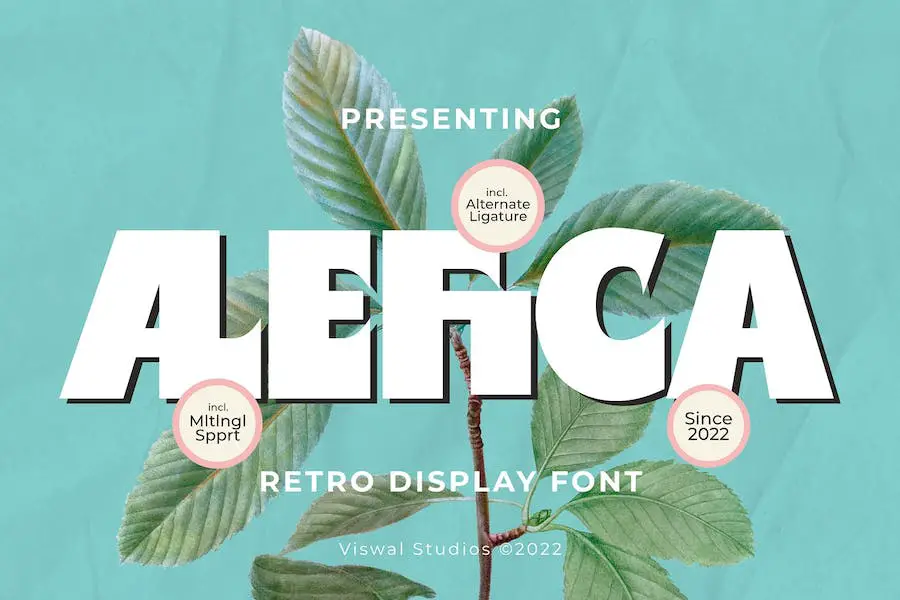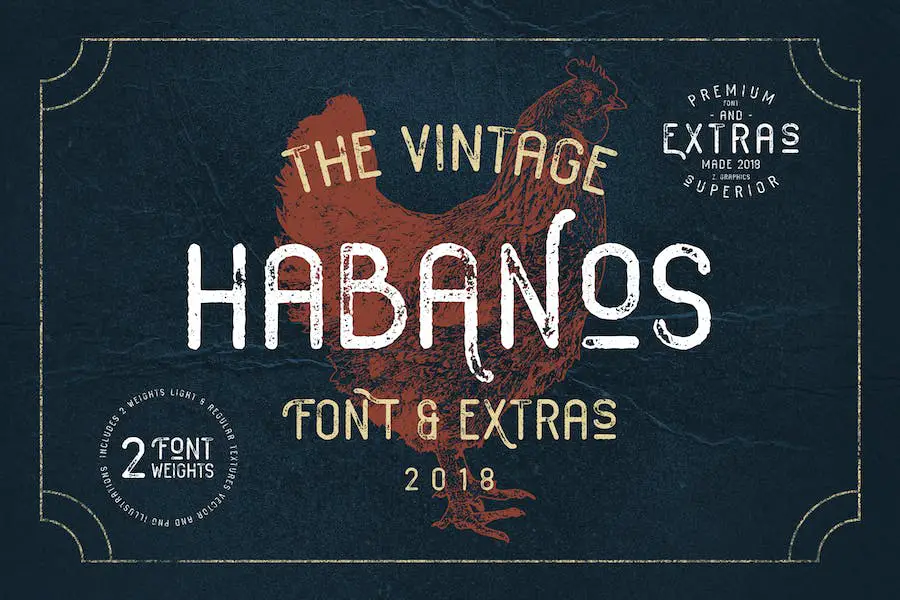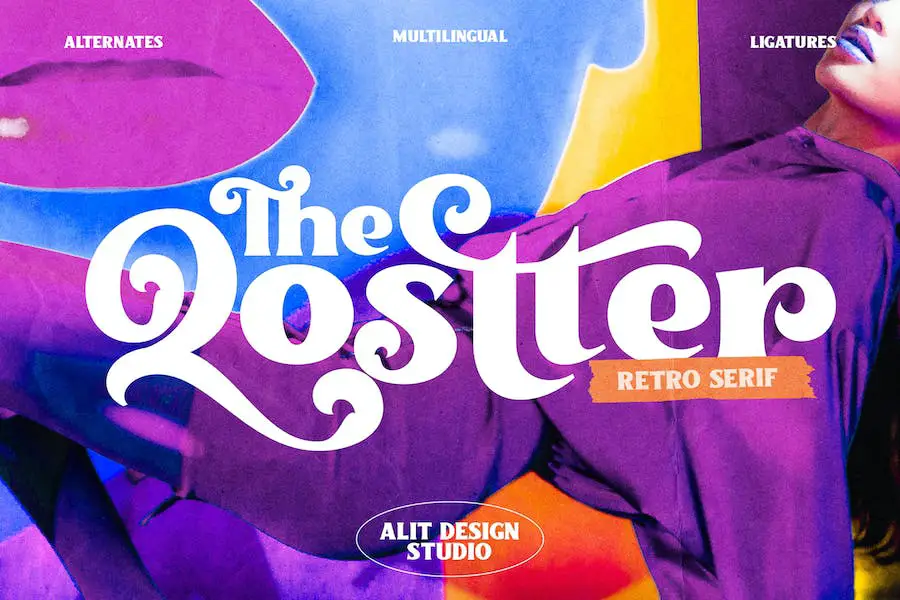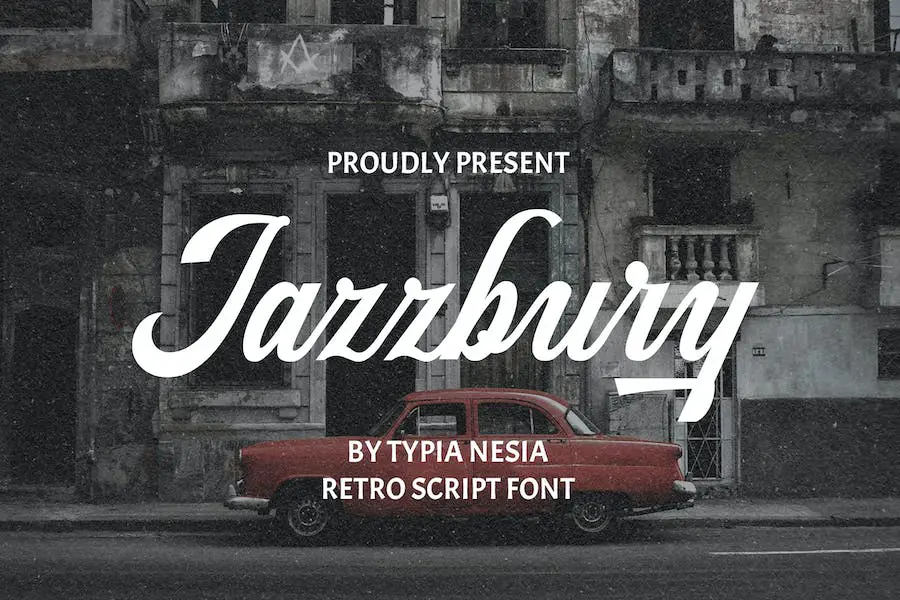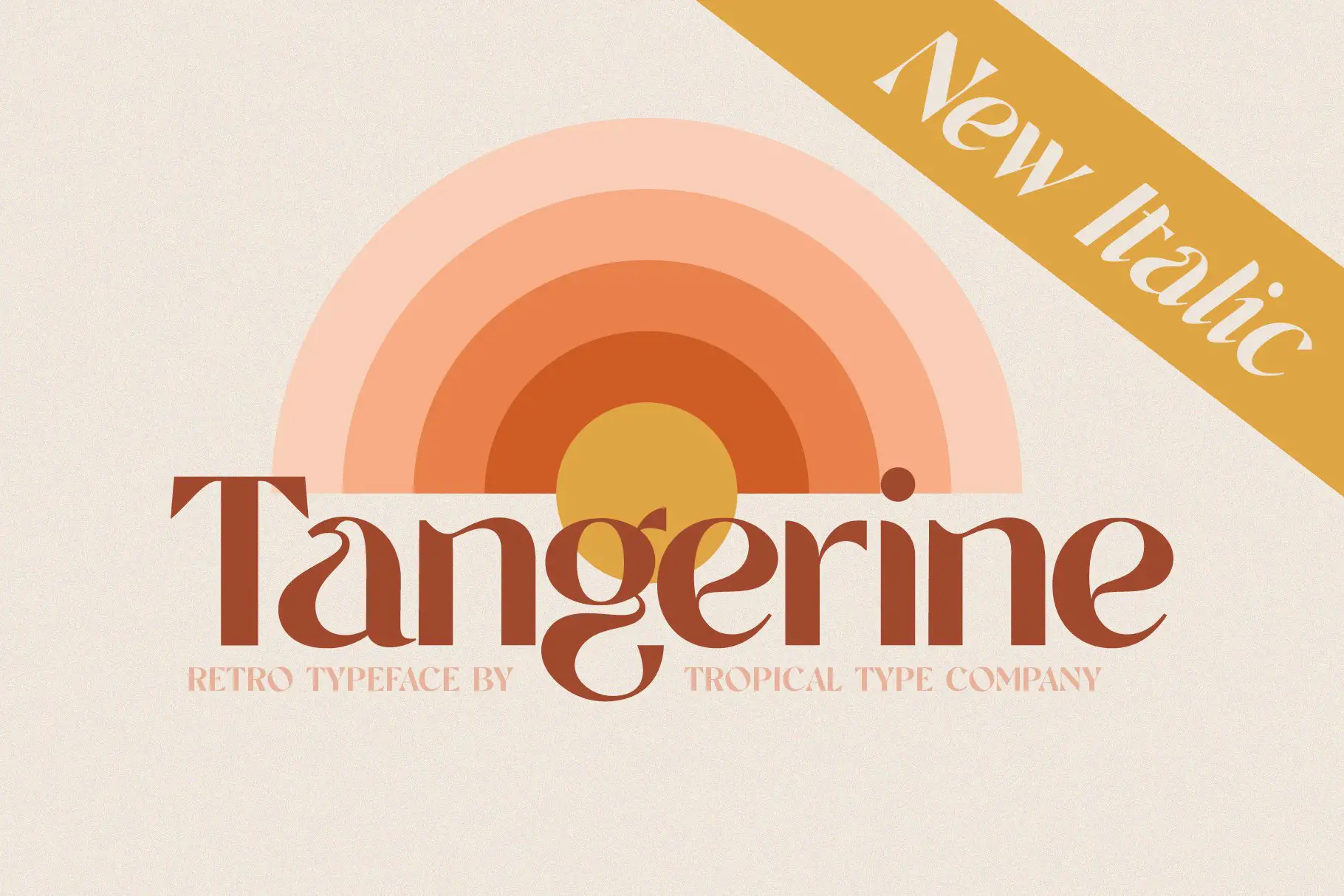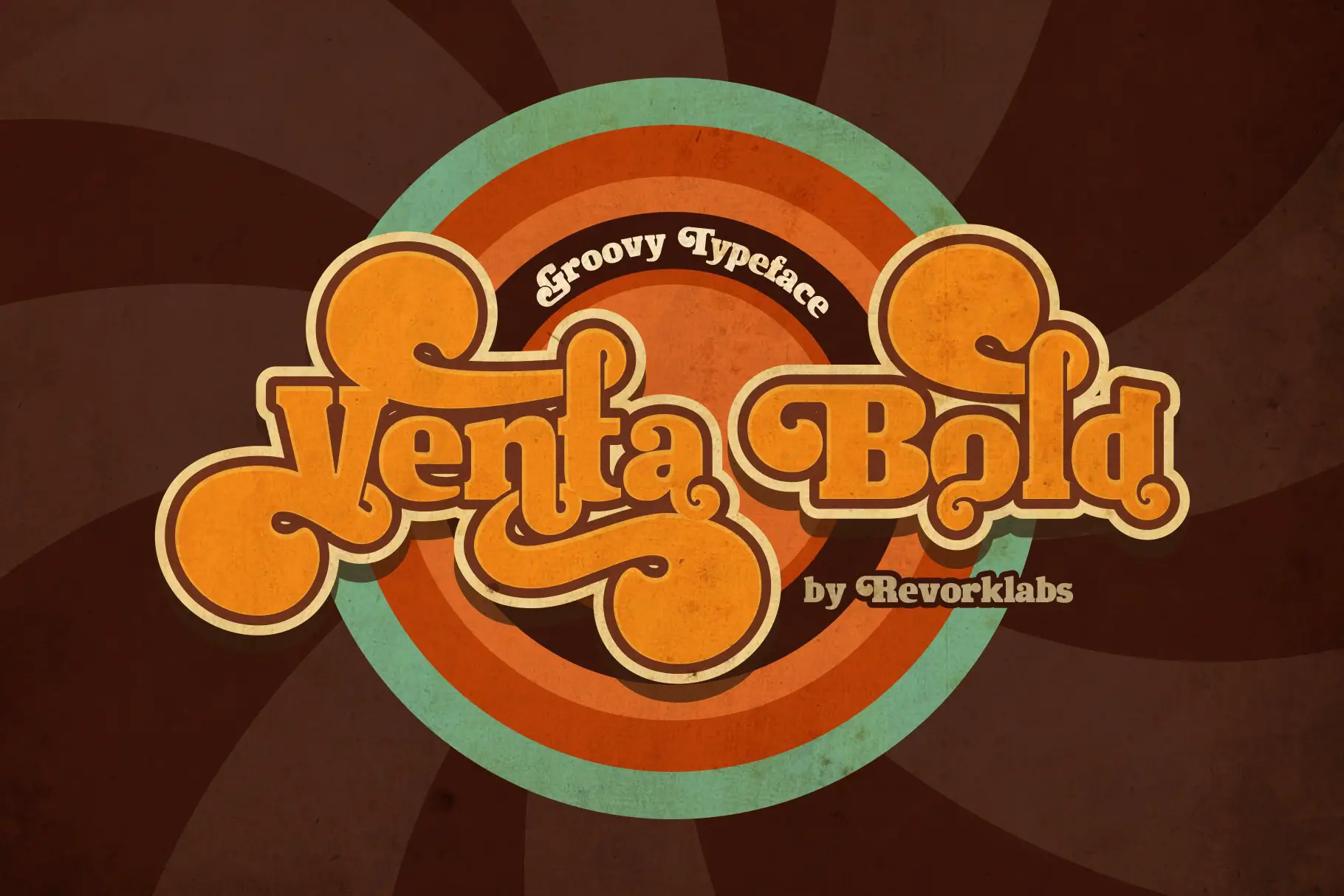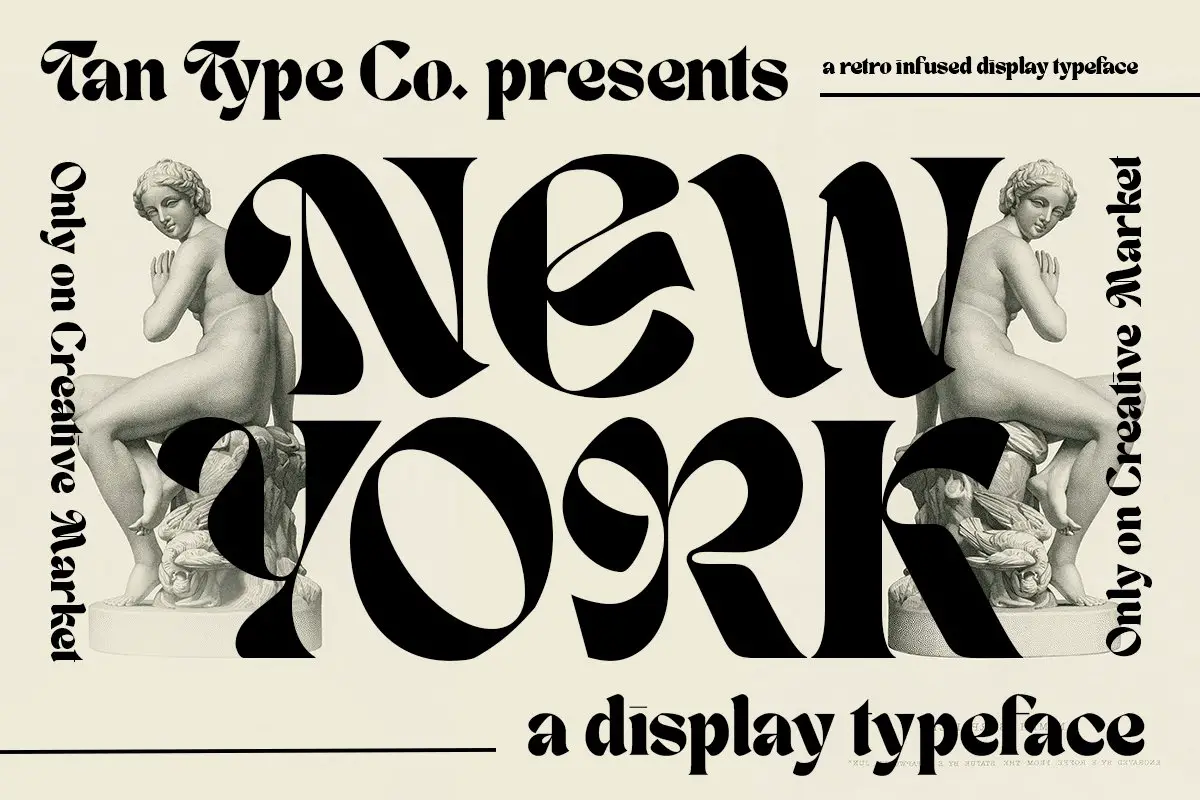
Die 36 besten Retro-Schriftarten 2023 (kostenlos und Premium)
Veröffentlicht: 2023-05-21Möchten Sie Ihren Designs etwas Retro-Flair verleihen und sie von der Masse abheben? Suchen Sie nicht weiter, denn wir haben für Sie eine Liste der 36 besten Retro-Schriftarten zusammengestellt!
In diesem Artikel stellen wir eine handverlesene Auswahl der besten Retro-Schriftarten vor, die derzeit auf dem Markt erhältlich sind.
Diese Schriftarten wurden sorgfältig aufgrund ihrer Beliebtheit, Vielseitigkeit und Ästhetik ausgewählt. Egal, ob Sie an einem Branding-Projekt, einem Posterdesign oder einem Website-Layout arbeiten, diese Schriftarten verleihen Ihrer Arbeit mit Sicherheit das gewisse Etwas.
Was genau ist also eine Retro-Schriftart? Eine Retro-Schriftart ist eine Schriftart, die von einer bestimmten Epoche oder einem bestimmten Stil aus der Vergangenheit inspiriert wurde.
Diese Schriftarten werden oft in Vintage- oder Retro-Designs verwendet, können aber auch in moderneren Designs verwendet werden, um ihnen ein einzigartiges und nostalgisches Gefühl zu verleihen. In diesem Artikel erkunden wir eine große Auswahl an Retro-Schriftarten, darunter Art Deco, Mid-Century Modern und von den 1970er Jahren inspirierte Designs.
Also lasst uns anfangen!
Beste Premium-Retro-Schriftarten
In diesem Artikel stellen wir eine handverlesene Auswahl der besten Retro-Schriftarten vor, die heute auf dem Markt erhältlich sind. Diese Schriftarten wurden sorgfältig aufgrund ihrer Beliebtheit, Vielseitigkeit und Ästhetik ausgewählt.
Egal, ob Sie an einem Branding-Projekt, einem Posterdesign oder einem Website-Layout arbeiten, diese Schriftarten verleihen Ihrer Arbeit mit Sicherheit das gewisse Etwas.
In diesem Artikel erkunden wir eine große Auswahl an Retro-Schriftarten, darunter Art Deco, Mid-Century Modern und von den 1970er Jahren inspirierte Designs. Also lasst uns anfangen!
Rambors
Rambors ist eine mehrzeilige Displayschrift, die das flippige und futuristische Design der 70er-Jahre verkörpert. Diese Schriftart wirkt nostalgisch und zugleich zeitgenössisch und eignet sich daher perfekt für modern-futuristische Designs.
Eines der besten Features von Rambors sind die wechselnden Charaktere, die den Benutzern mehr Möglichkeiten zur individuellen Gestaltung ihrer Designs bieten. Diese Schriftart ist ideal für diejenigen, die nach Vintage-Schriftarten suchen, um ihren Projekten einen Hauch von Nostalgie zu verleihen und gleichzeitig eine moderne Atmosphäre zu bewahren.
Derphace
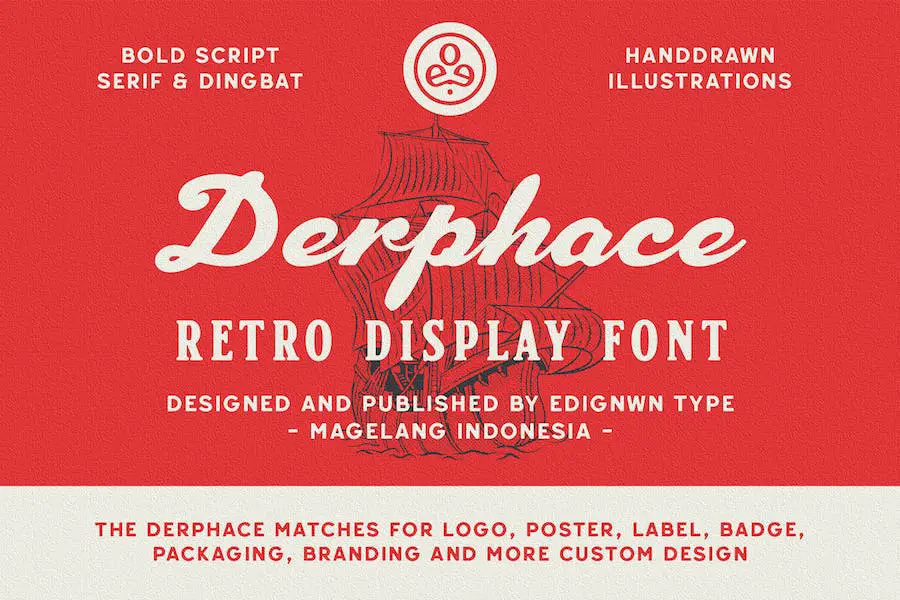
Derphace Font ist die perfekte Wahl für alle, die eine Schriftartensammlung im Retro-Stil suchen, um ihre individuellen Designprojekte aufzuwerten. Diese Schriftart ist von den alten Etiketten inspiriert und verfügt über Skript- und Serifenschriftstile.
Derphace Font umfasst vier einzigartige Schriftarten: Regular, Rounded, Rough und Stamp. Darüber hinaus bietet diese Schriftartensammlung zusätzliche Illustrationen zu nautischen und Piratenthemen in einem Paket.
Die Schreibschrift von Derphace bietet auch einige Alternativen, die für die Erstellung auffälliger Logos, Poster, Etiketten, Abzeichen, Verpackungen, Brandings, Zitate und mehr nützlich sein können. Seine Vielseitigkeit und vielfältigen Stiloptionen machen es zu einem Muss für jeden Designer, der nach Adobe Retro-Schriftarten sucht.
KABOORE
Kaboore ist eine neue Retro-Schriftart, die sich perfekt für Grafikdesigner eignet, die ihre Projekte aufwerten möchten. Es ist in einem kompakten Stil erhältlich und bietet sowohl Platten- als auch Sans-Optionen, was es vielseitig für verschiedene Designanforderungen macht.
Wenn Sie nach Retro-Schriftarten für Canva suchen, schauen Sie sich unbedingt Kaboore und Rambors an. Diese Schriftarten verleihen Ihren Designs ein einzigartiges und auffälliges Aussehen, das perfekt ist, um die Aufmerksamkeit des Betrachters zu erregen.
Starker Westen
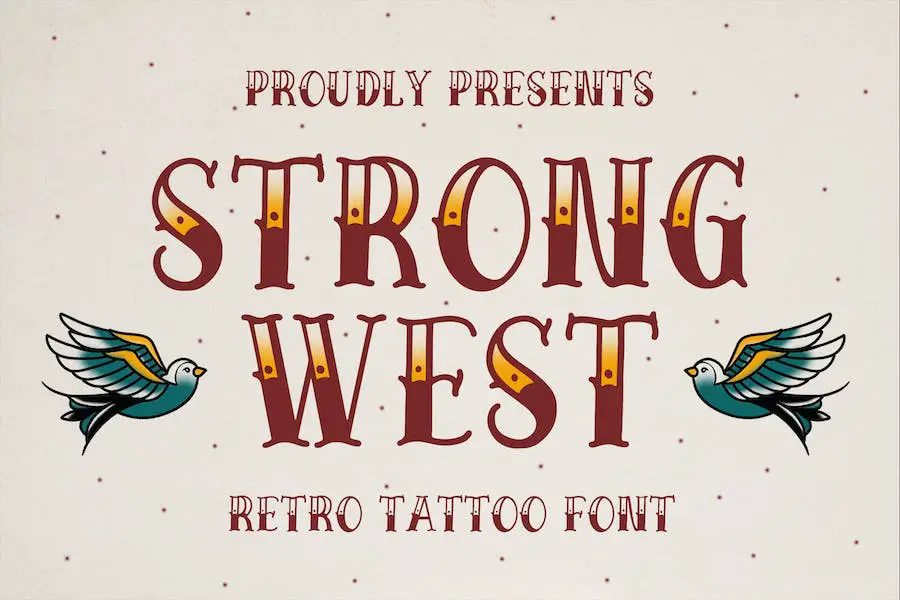
Strong West ist eine neue Script-Schriftart, die Ihren Designprojekten ein Retro-Feeling verleiht. Diese einzigartige Schriftart bietet ein unverwechselbares Aussehen und eignet sich perfekt für Logos, Friseursalons, Abzeichen, Tätowierer, Tattoo-Artikel, Tattoo-Buchstaben und mehr.
Ein weiteres großartiges Merkmal von Strong West ist seine Vielseitigkeit. Egal, ob Sie ein Logo entwerfen oder Waren für ein Tattoo-Unternehmen erstellen, diese Schriftart passt genau dazu. Sie funktioniert gut mit verschiedenen Design-Software, einschließlich Figma, und ist daher eine gute Wahl für Designer, die nach Retro-Schriftarten für Figma suchen.
Retro krank
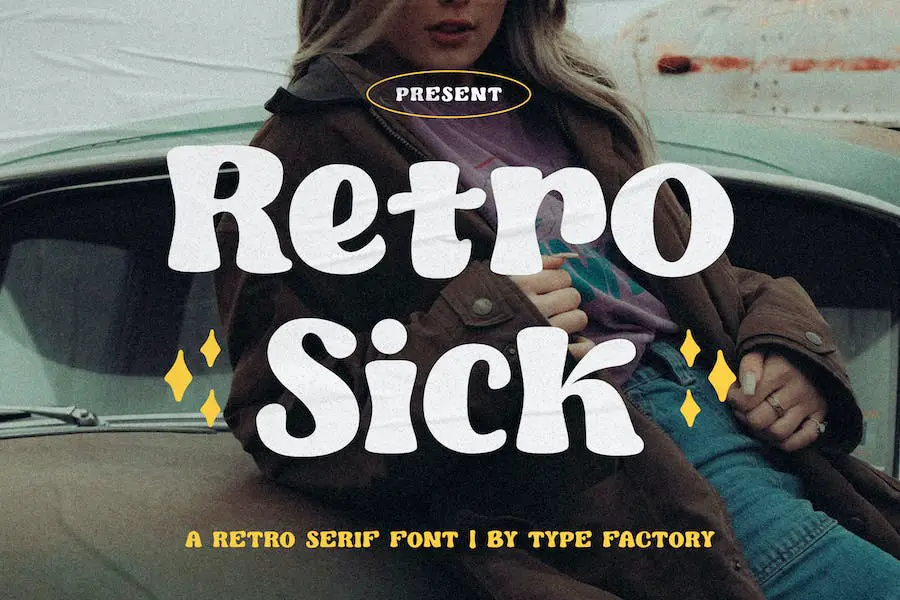
Retro Sick ist eine atemberaubende Serifenschrift, die der klassischen Retro-Ästhetik eine moderne Note verleiht. Diese Schriftart ist perfekt für diejenigen, die Designs erstellen möchten, die sich durch ihre einzigartigen und gewagten Eigenschaften von der Masse abheben. Sein zeitloser Reiz macht es zu einer vielseitigen Option für eine Vielzahl von Projekten, die eine besondere Note erfordern.